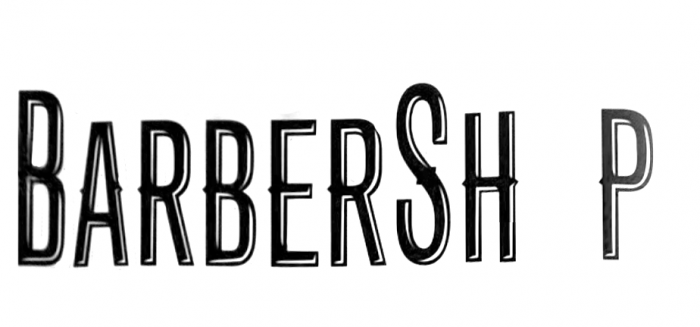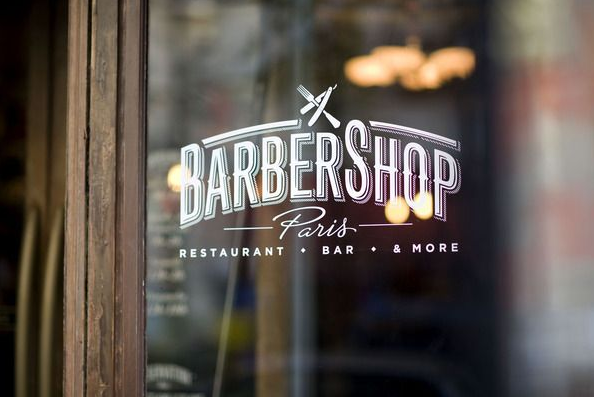
Welche schrifft ist das?
mal gucken ob ihr mir helfen könnt, ich suche die schrift im bild mit dem wort barbershop, kennt die jemand??
Ich hab das mal grade gerückt und den Schatten entfernt …
Yes Gizzmo, I think the grotesque extra condensed comes very close to it, some last touches with illustrator and done, I also like the underlayed layer with the filled in texture, it makes the design so much vintage and nostalgic....